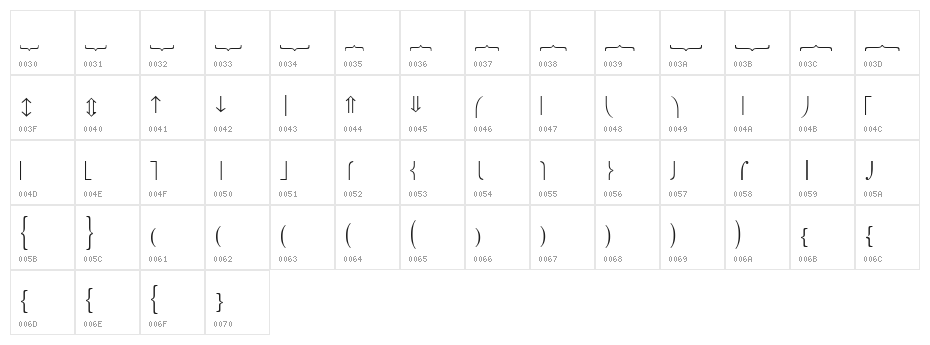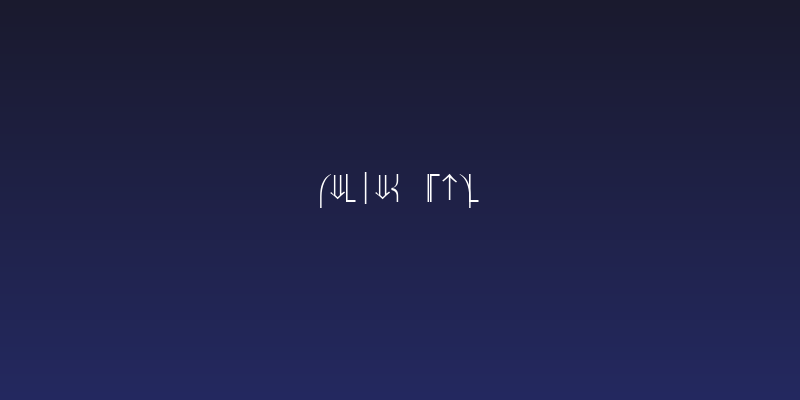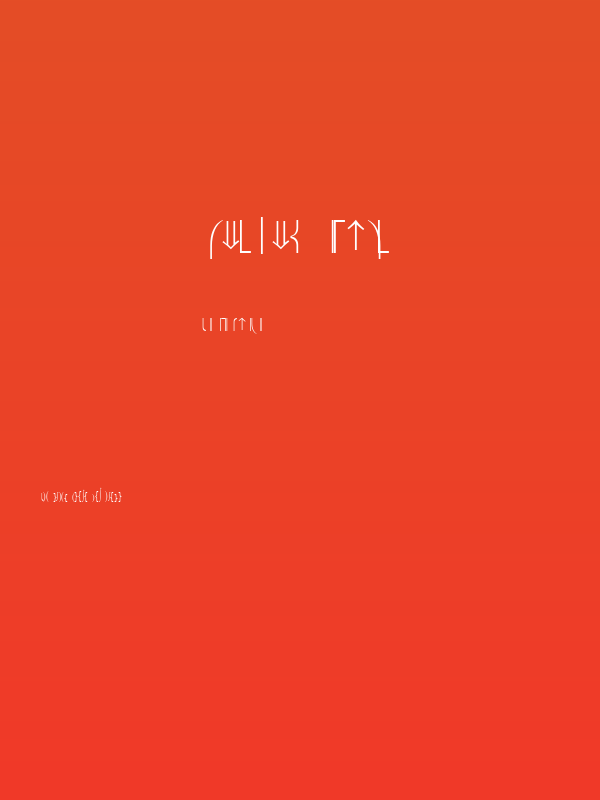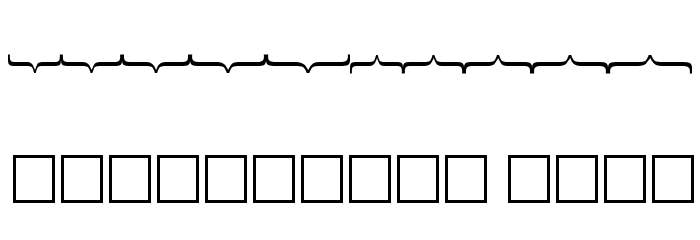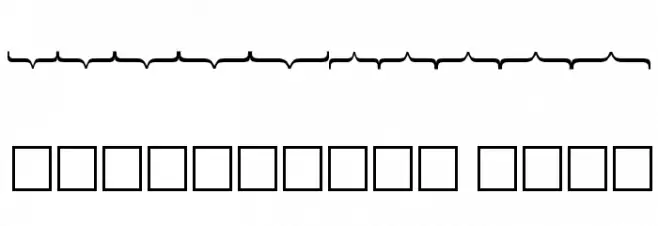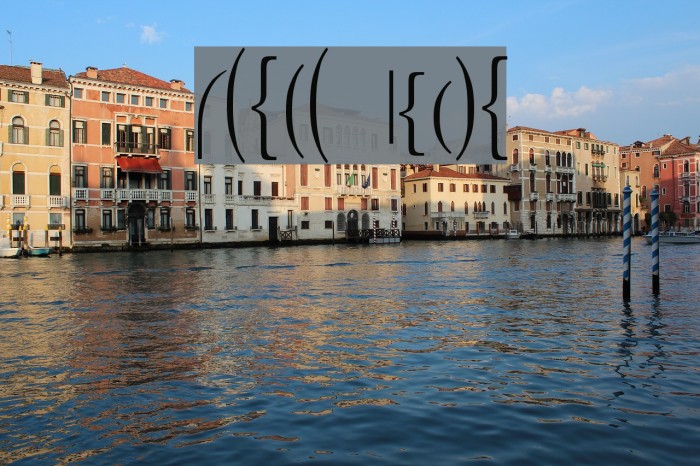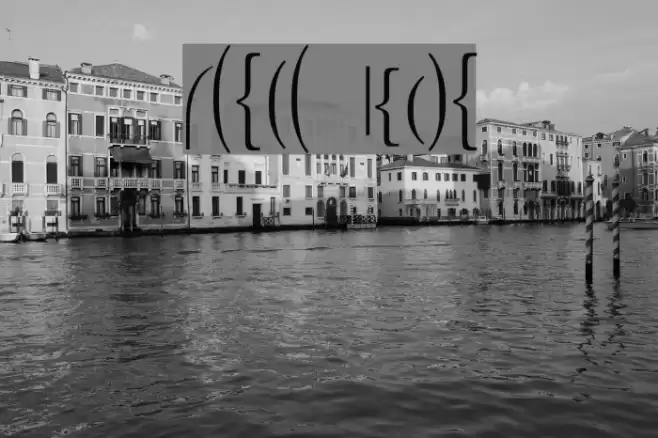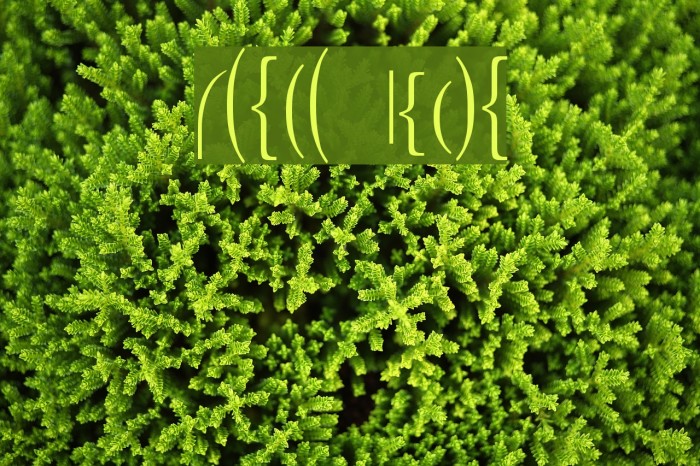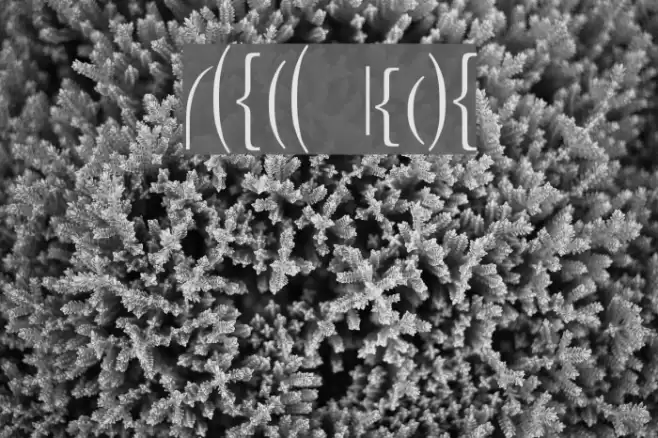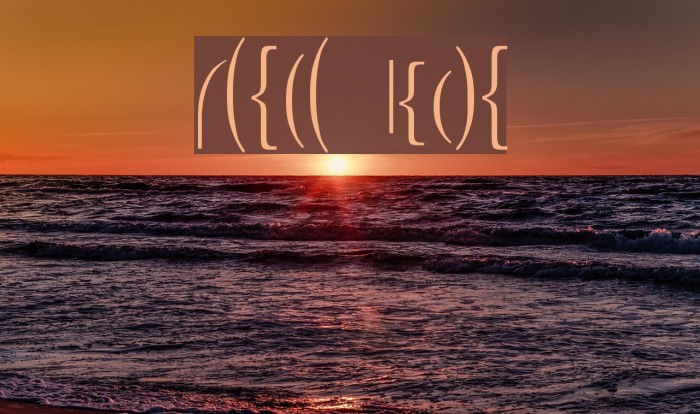
Fences Plain Font
| Gesamtstil | Modern, Decorative |
| Anwendungsfall | Logos, Artistic projects, Graphic design elements |
| Vorgeschlagene Projekte | This design is ideal for artistic projects, graphic design elements, logos, and creative branding where a unique and abstract aesthetic is desired. |